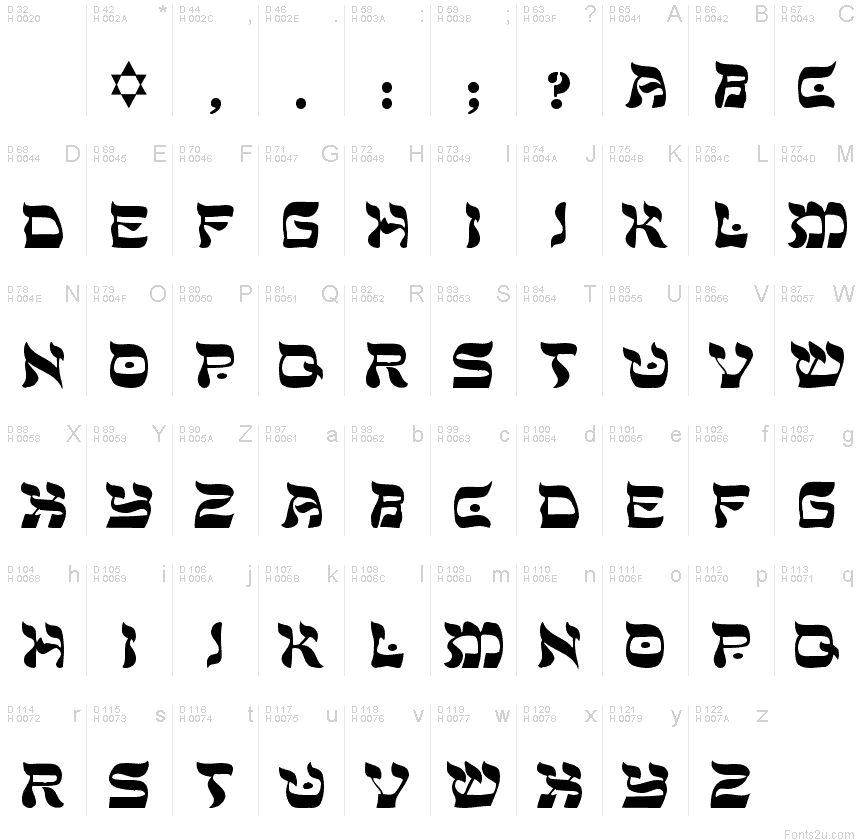
Peace to darmowy krój displayowy inspirowany stylem hebrajskim, wyróżniający się szerokimi, „atramentowymi” formami, które rozszerzają się ku górze i zwężają w zaokrąglone, wiszące zakończenia. Ta powtarzalna sylwetka nadaje literom rzeźbiony, ceremonialny charakter, a głębokie wewnętrzne wcięcia sprawiają, że ciemna masa nie wydaje się płaska ani ciężka.
Krój ten doskonale sprawdzi się na plakatach wydarzeń kulturalnych, ulotkach synagogalnych lub świątecznych, szyldach księgarni, okładkach albumów oraz na opakowaniach, wszędzie tam, gdzie historyczne nawiązanie do hebrajskiej typografii jest częścią języka wizualnego. Efektowne wielkie litery i wiszące formy małych liter świetnie komponują się w krótkich nagłówkach i logotypach, nadając zwartemu tekstowi formalny, niemal emblematyczny ciężar.
Peace